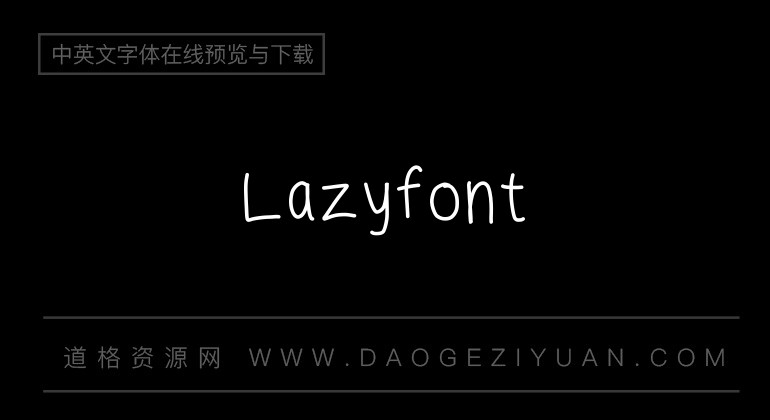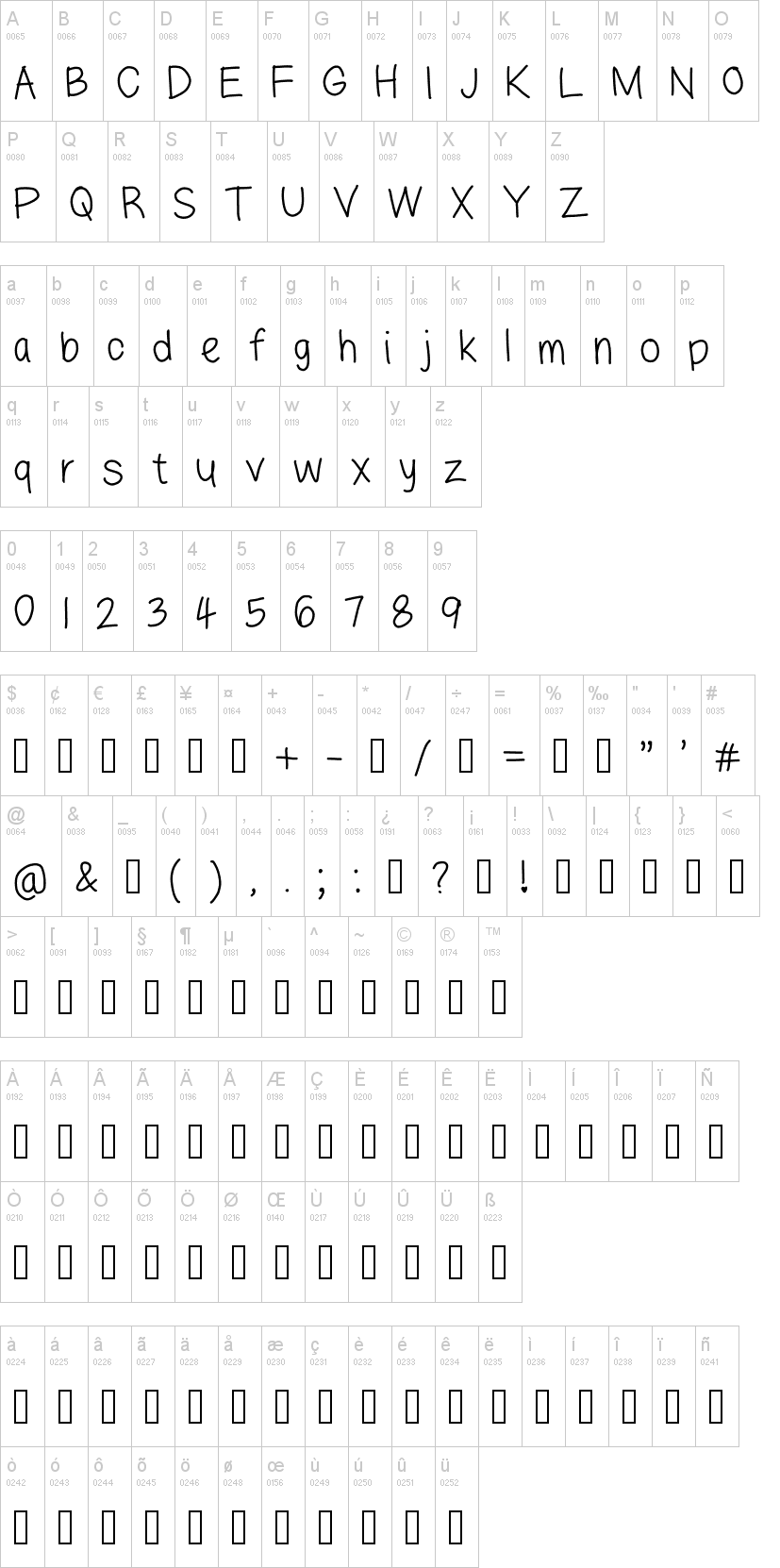
? Lazyfont 字体是一款简洁、优雅、易读的字体,它具有平衡的线条、明显的空间感和多变的节奏感。它的字体风格融合了现代设计和传统技术,具有良好的可读性,适合用于各种文档、网页、平面设计等。内容介绍
Lazyfont是一款非常不错的手写艺术字体,具有很好的视觉感,适合于文化类的宣传设计、商业类品牌的广告和产品包装设计以及个性化文字排版等较多场景。